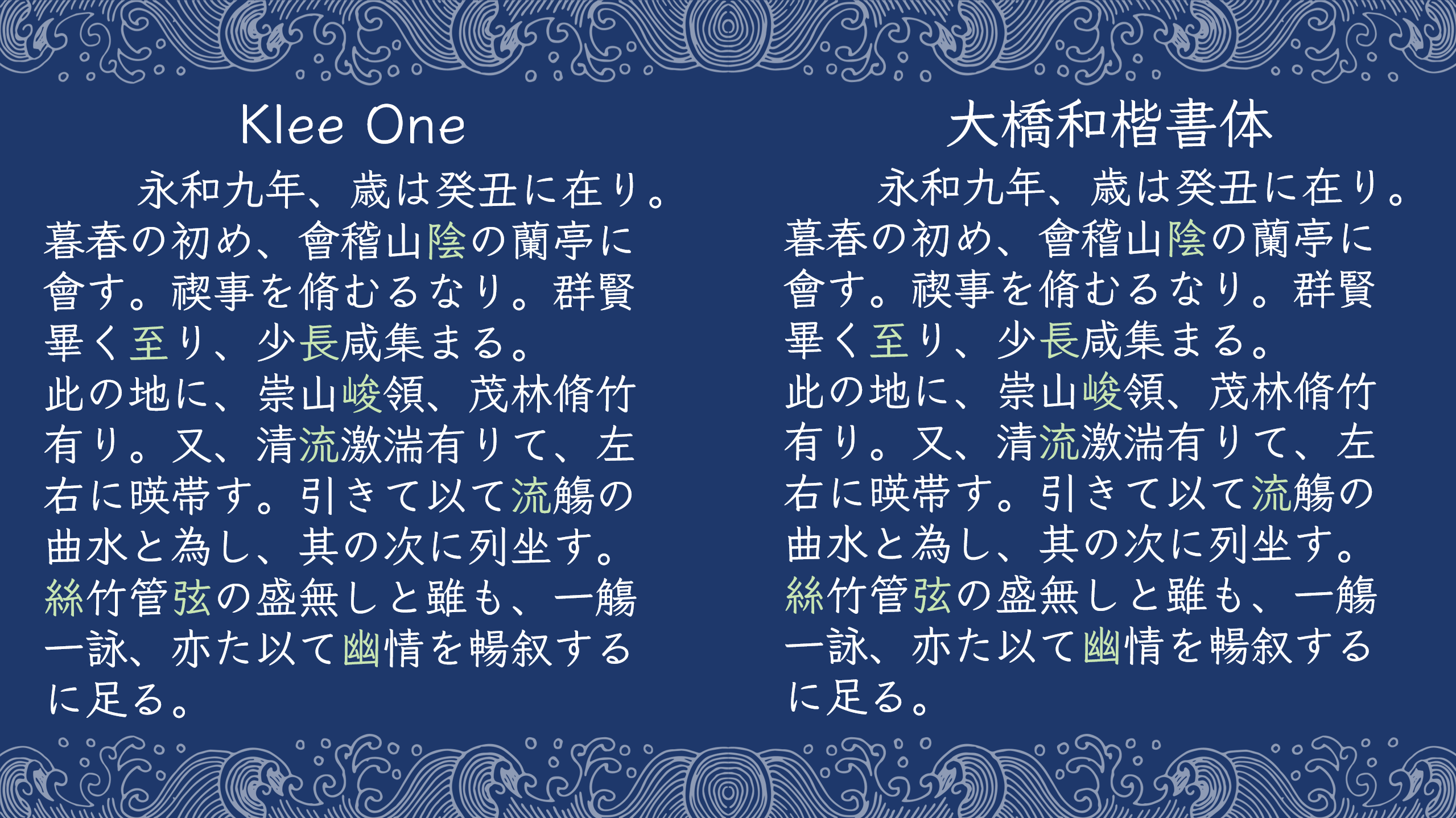
大桥和楷书体
An open-source Japanese handwriting font derived from Fontworks’ Klee One. 一款开源日文手写字体,基于 FONTWORKS 出品字体 Klee One 衍生。
Fontworks将Klee One字体开源后,网络上逐渐出现了霞鹜文楷GB、芫荽、芫茜雅楷等贴近各地标准手写字形的字体。Klee One本身笔画造型较为贴近日本学参常用的「教科书体」风格,但其字形更接近印刷体。为了让日语学习者能更好地了解日本标准的手写字形,同时也让日本用户有一种更贴近手写字形的选择,使该字体拥有更广泛的使用场景,本人在此基础上借鉴霞鹜文楷、霞鹜文楷GB、芫荽、Y式笔书体等字体,将Klee One修改成尽可能贴近日本学参标准的字形,以适合日文教学等用途。因本字体主要用途为排版日文或展示日本学参书写字形,故以代表日本主体民族的「和」字命名为「和楷」。
考虑到本字体可能作为手机显示字体,可能存在需要与简体中文混排的场景,本人在Klee One的字数基础上,使用霞鹜文楷、霞鹜文楷GB为此字体补全了通用规范汉字表的字数,并将这些字形进行调整,如按照现实或假想的日本标准进行类推,使得混排时风格能够统一。后期会合并霞鹜文楷GB等字以体继续扩充字符数量,但暂无全部改完的计划。